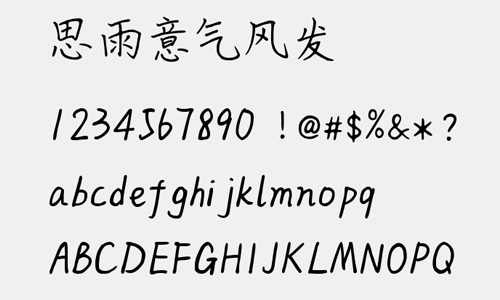
思雨意氣風(fēng)發(fā)字體是思雨字庫(kù)推出的一款硬筆手寫(xiě)藝術(shù)字體,臥中,談山河萬(wàn)里。跨白馬,行十里長(zhǎng)街。該字體是在國(guó)家標(biāo)準(zhǔn)簡(jiǎn)體字庫(kù)GB2312所包含6763漢字的基礎(chǔ)上,又增加了近200常用字,已經(jīng)覆蓋了大陸99.75%的漢字使用頻率,足以滿足日常需求。歡迎喜歡思雨意氣風(fēng)發(fā)字體的朋友前來(lái)下載使用。